随着艺术字体设计在线生成软件和各类设计平台的问世,为艺术字行业的发展添砖加瓦,可以注意到诸如字体视界平台收集了诸多令人追捧的特殊艺术字体,一些收缩紧靠,一些大方庄重,总体来说搭配协调,展示出了不同的字体品格,有疏有密,各具特色,那为什么艺术字体设计在线生成字体受欢迎呢,为什么许多品牌也进行在线设计?
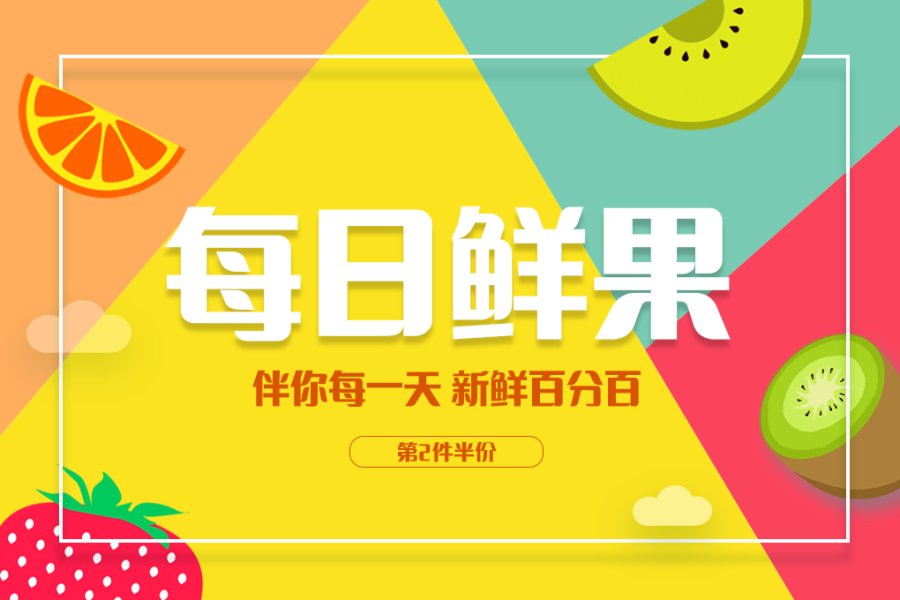
英文和中文的结合,是艺术字体设计在线生成的诀窍之一,前后连贯有延续,避免消费者(或个人设计者)抵触和排斥图形logo,在强调用中文艺术字、英文艺术字或是中英文艺术字作为结合的时候,它所表达的东西是更为直接、更为纯粹,更为有效,艺术字设计在其它方面的重要性不言自明,比如说海报、包装、slogan,也有诸多设计的范例。比如蓝月亮还有雪碧,当我们看到这类包装的时候,是非常清楚的能够辨别出它是什么品牌,因为它的艺术字画面占用的比例高,一个好的包装艺术字必须要做的非常准确、非常突出,当一个艺术字做的非常好的时候,整个包装就显得不那么单调。
艺术字体设计在线生成图形符号融入艺术字里边,可以非常巧妙的把主题表现出来,我们可以想象一下,如果并无艺术字设计行业,只是单纯的用黑体字来做,它的表现的力度就非常平庸,优质的艺术字设计容易吸引我们的眼球,从而引起我们的点击和购买,这也是艺术字设计的功效。